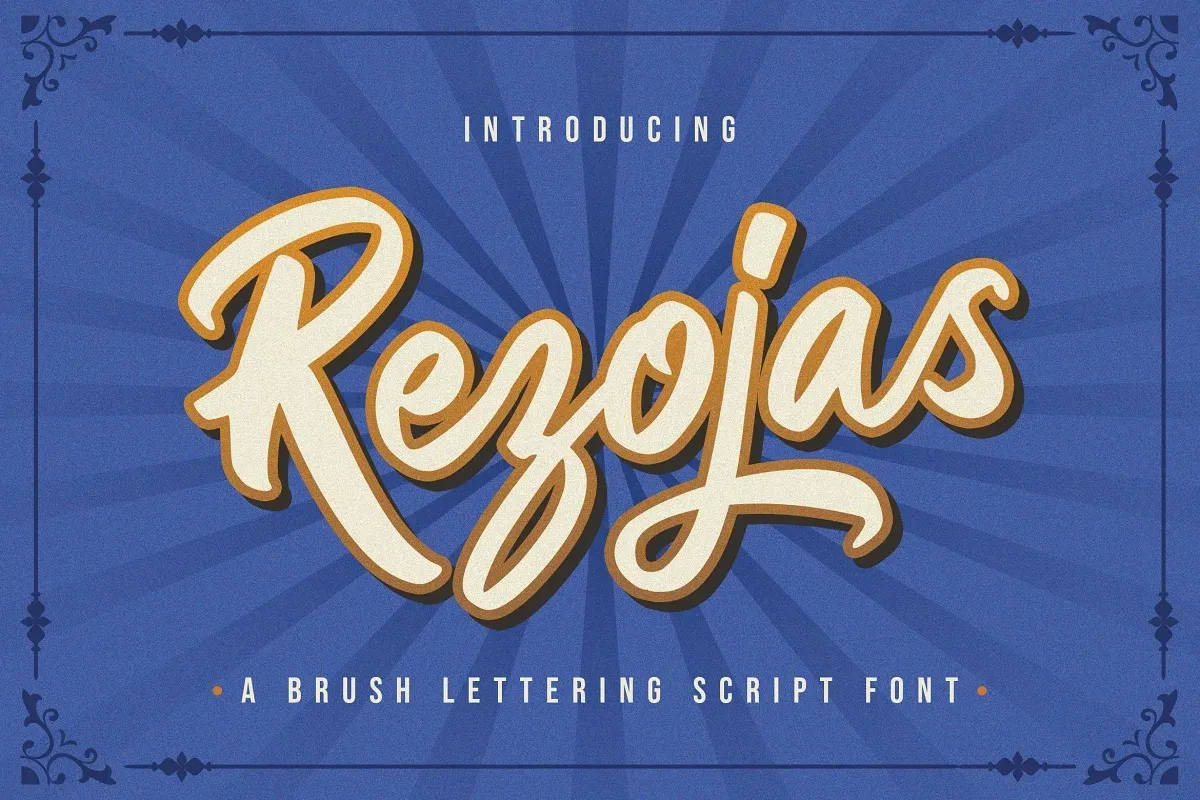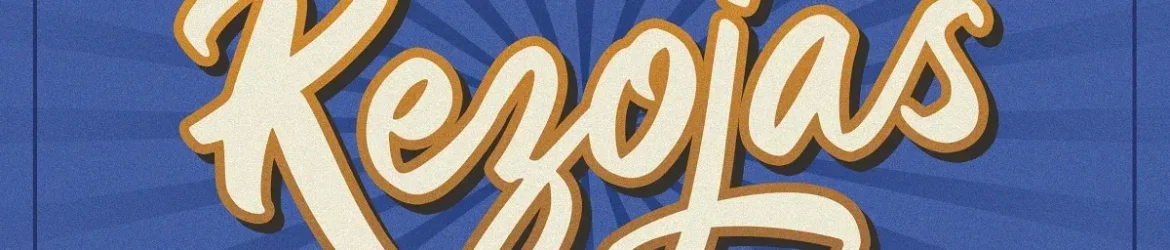
Esta é uma fonte bold retro script com traços dinâmicos e bonitos, criada pelo font designer StringLabs. Conforme descrito na descrição original, a Rezojas Font tem um estilo vintage único que se destaca por sua curvatura e forma arredondada. É perfeita para criar marcas de marca, oferecendo uma textura vitoriosa que dá vida às suas ideias mais criativas. Apenas imagine como essa font pode revolucionar a forma como você expressa sua identidade visual. Add it to your next project and watch as it transforms every design into a masterpiece!